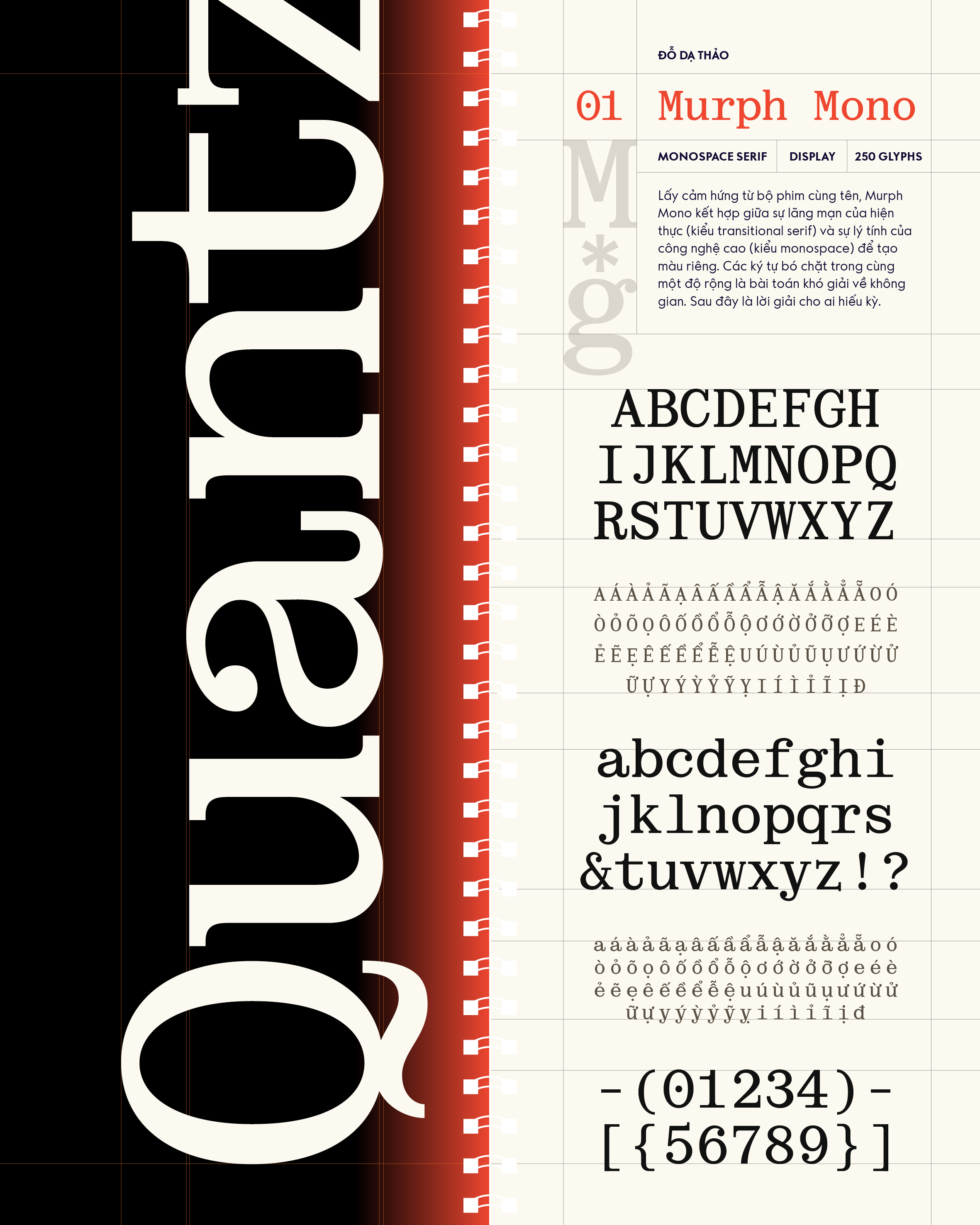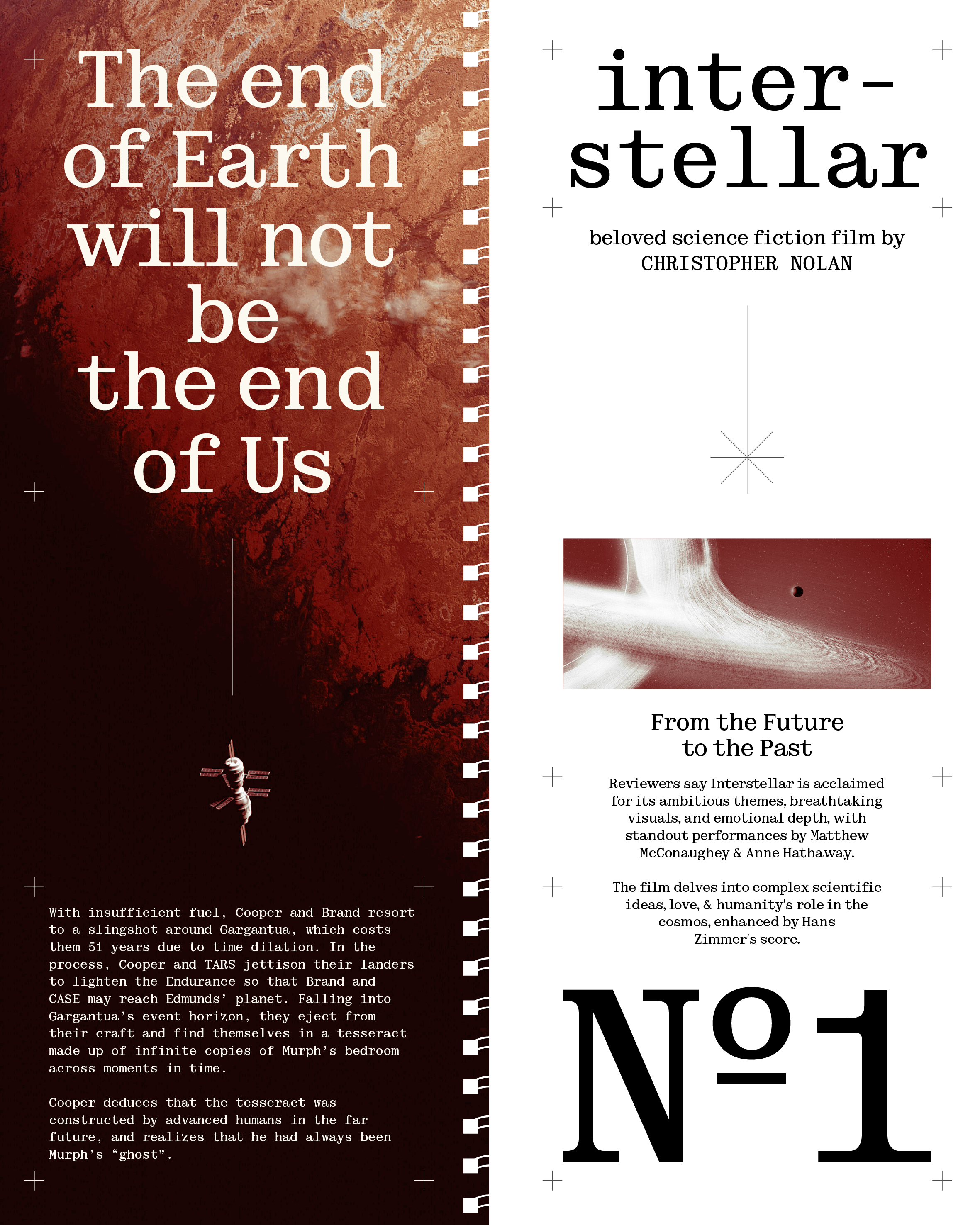
Murph Mono
Về Murph Mono: Lấy cảm hứng từ bộ phim cùng tên, Murph Mono kết hợp giữa sự lãng mạn của hiện thực (kiểu transitional serif) và sự lý tính của công nghệ cao (kiểu monospace) để tạo màu riêng. Các ký tự bó chặt trong cùng một độ rộng là bài toán khó giải về không gian. Sau đây là lời giải cho ai hiếu kỳ.
Đỗ Dạ Thảo